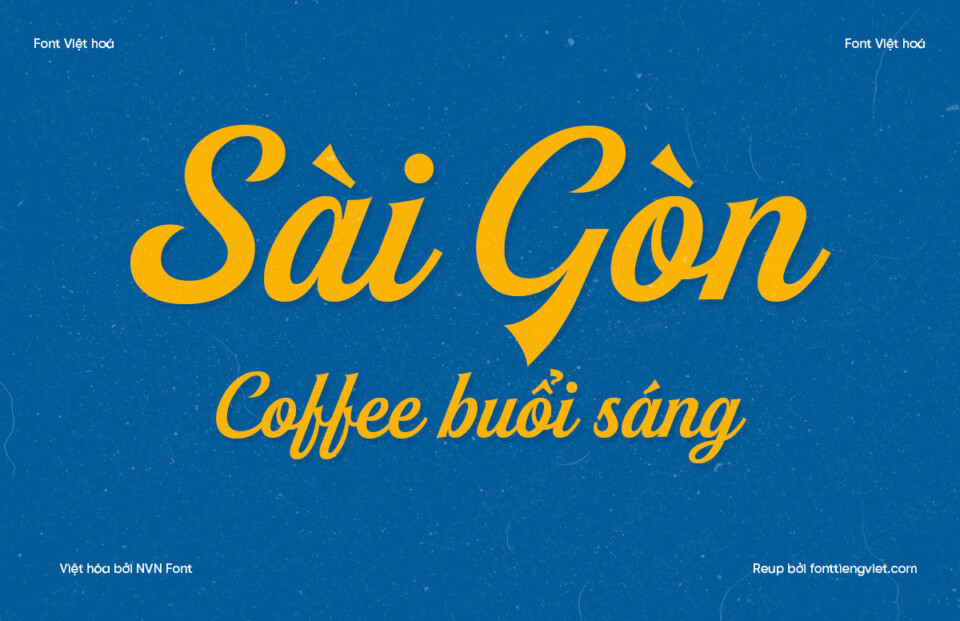
Giới thiệu về Font Việt hóa NVN Buinton
Trong thế giới đồ họa hiện đại, việc tìm kiếm một bộ Font Chữ vừa mang nét cổ điển vừa giữ được sự tinh tế là điều không hề dễ dàng. Font Việt hóa NVN Buinton chính là giải pháp hoàn hảo dành cho các nhà thiết kế đang tìm kiếm sự phá cách. Đây là một phông chữ dạng script với những đường nét uốn lượn mạnh mẽ, lấy cảm hứng từ phong cách retro và vintage của những thập niên trước. Với sự hỗ trợ đầy đủ dấu tiếng Việt, bộ font này giúp bạn tự do sáng tạo mà không lo lỗi hiển thị.
Đặc điểm nổi bật của Font Việt hóa NVN Buinton
Thiết kế đậm chất nghệ thuật
Điểm thu hút nhất của Font Việt hóa NVN Buinton nằm ở các nét chữ dày dặn và độ nghiêng đặc trưng. Những chi tiết này tạo nên cảm giác thủ công, gần gũi nhưng không kém phần sang trọng. Phông chữ này rất phù hợp để sử dụng trong các dự án thiết kế logo, bao bì sản phẩm, hay các mẫu áo thun mang phong cách đường phố. Sự linh hoạt trong từng ký tự cho phép người dùng biến hóa đa dạng từ các tiêu đề ngắn đến những đoạn văn bản trang trí phức tạp.
Khả năng ứng dụng đa dạng
Không chỉ dừng lại ở các sản phẩm in ấn, Font Việt hóa NVN Buinton còn được ưa chuộng trong việc thiết kế ảnh bìa mạng xã hội hoặc các ấn phẩm truyền thông học đường. Với bộ ký tự mở rộng và các tính năng OpenType, bạn có thể dễ dàng tùy chỉnh các nét nối chữ để tạo ra dấu ấn riêng biệt cho tác phẩm của mình. Đây thực sự là công cụ đắc lực giúp nâng tầm thẩm mỹ cho mọi dự án đồ họa.